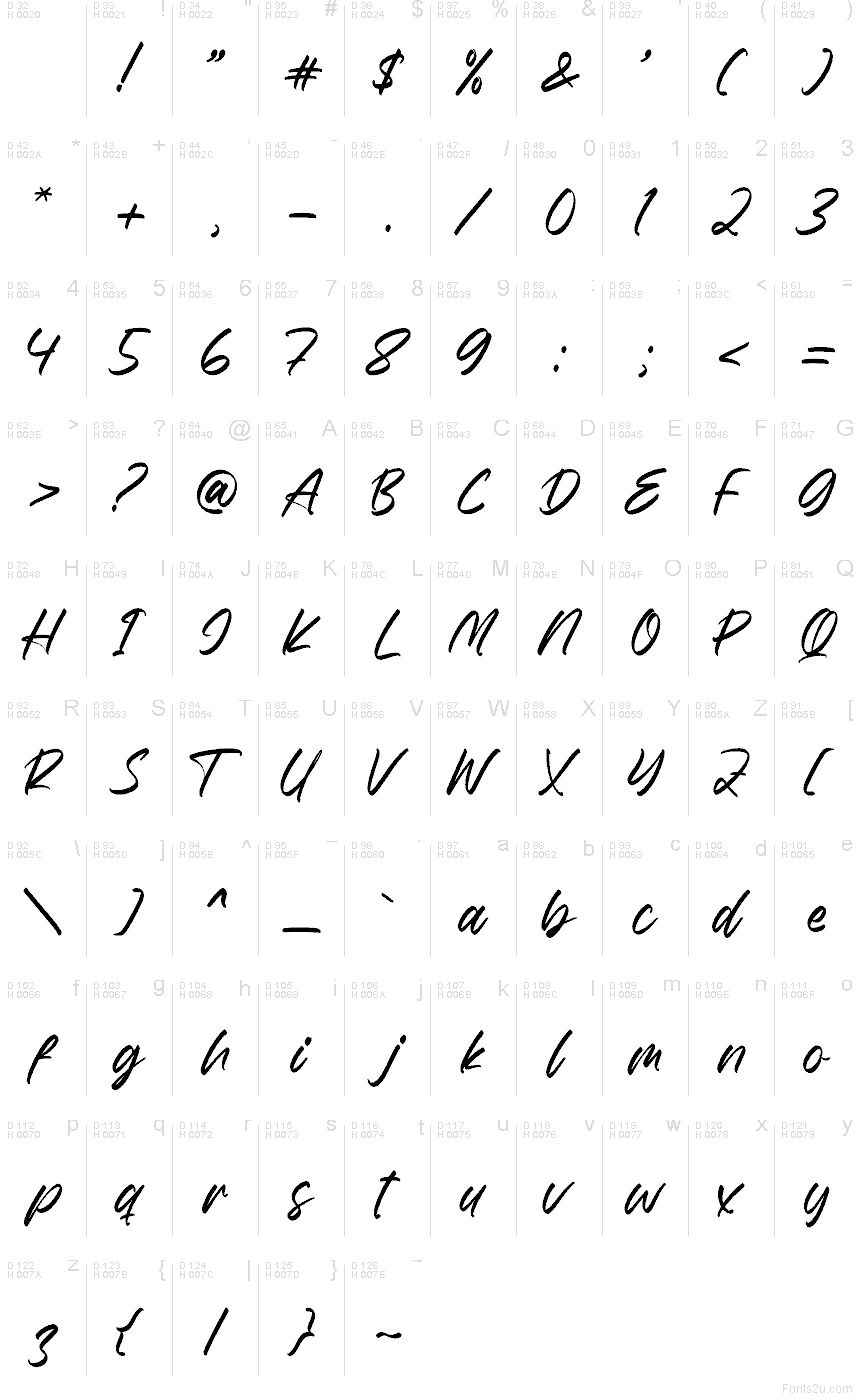
Wolenta Skyline od ErgibiStudio to darmowy krój pisma typu script, charakteryzujący się luźnym rytmem pędzla oraz wysokim, swobodnym stylem. Litery opierają się na długich, zapętlonych pociągnięciach i szybkich łączeniach, co nadaje całości charakteru szybkiego podpisu, a nie wypracowanej kaligrafii.
Świetnie sprawdzi się w brandingu, menu kawiarni, opakowaniach kosmetyków, postach w mediach społecznościowych i tytułach magazynów, gdzie ważniejszy od sztywnej formy jest osobisty akcent. Jako darmowy font, idealnie nadaje się również do kart tytułowych, imion na zaproszeniach czy krótkich grafik z cytatami, ponieważ wydłużone krzywe i lekkie połączenia nadają słowom dynamiki.